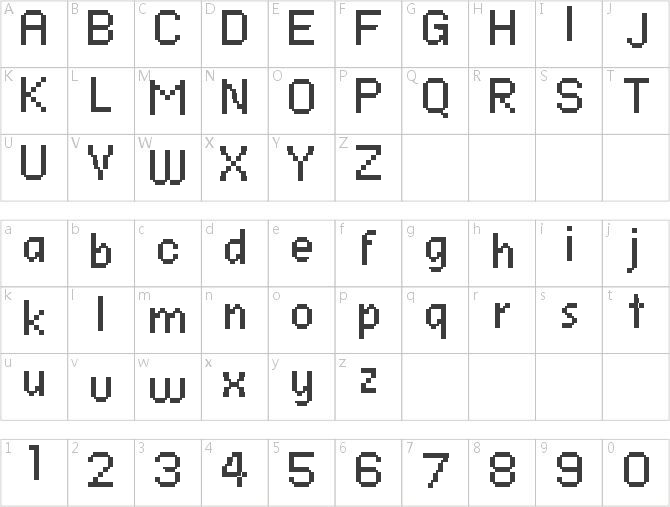
PF Ronda Seven
PF Ronda Seven介紹
PF Ronda Seven字體字庫是一款讓人賞心悅目、百看不厭的英文字體,適合各類廣告和產(chǎn)品包裝設(shè)計應(yīng)用,字體大小0.08MB,格式為ttf字體,上傳用戶是素年錦時,作者/版權(quán)方為未知